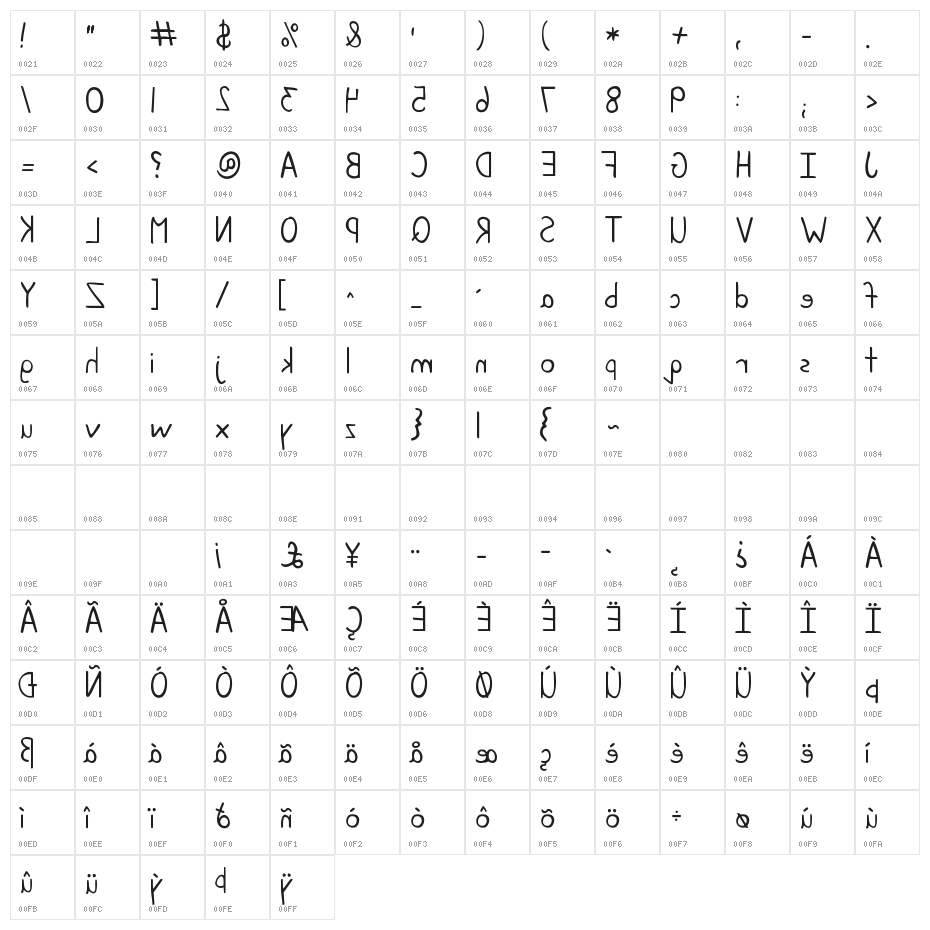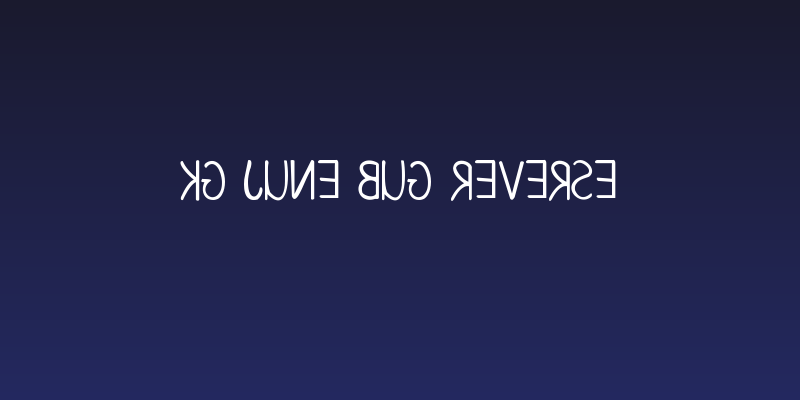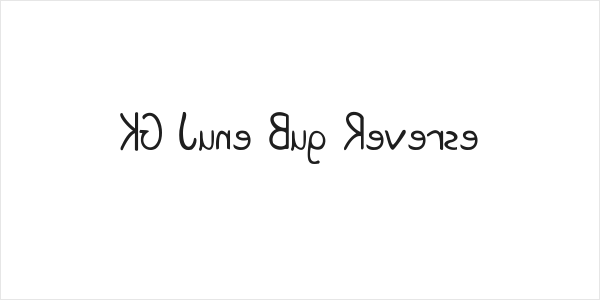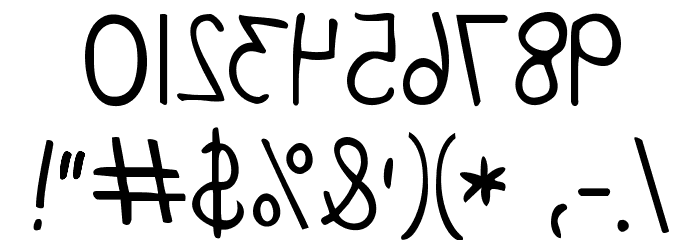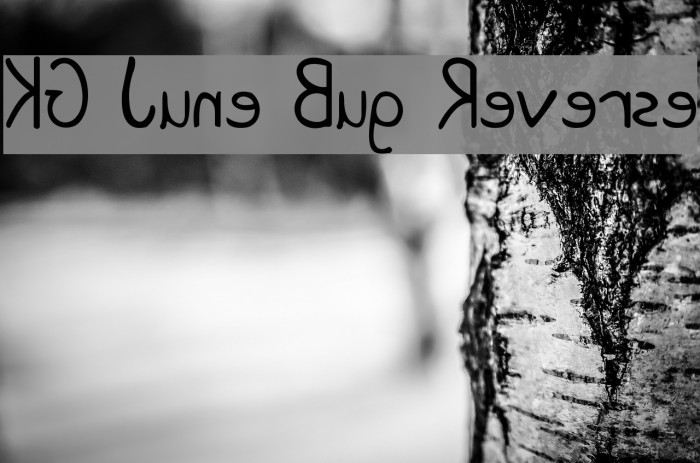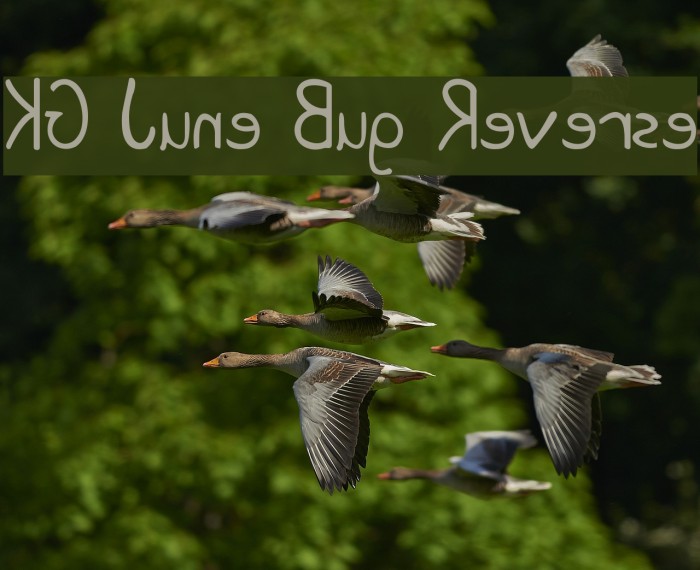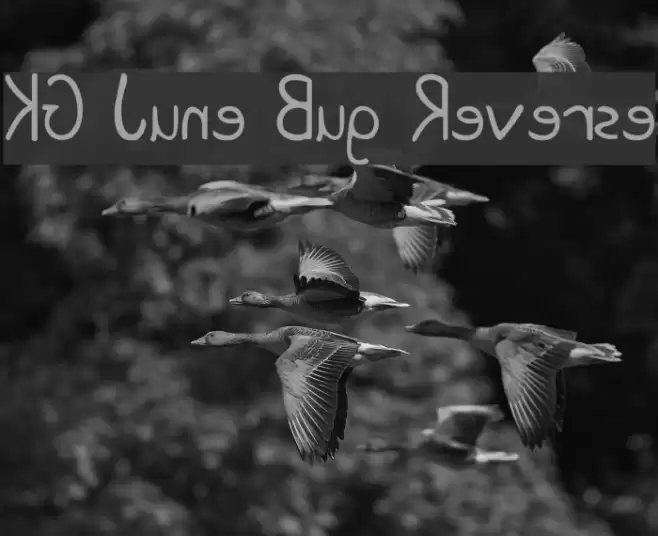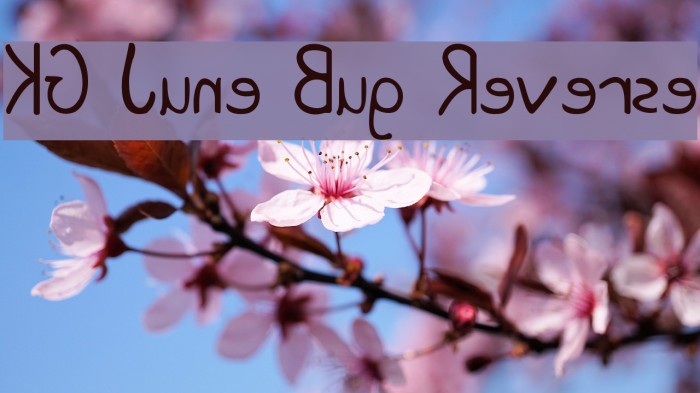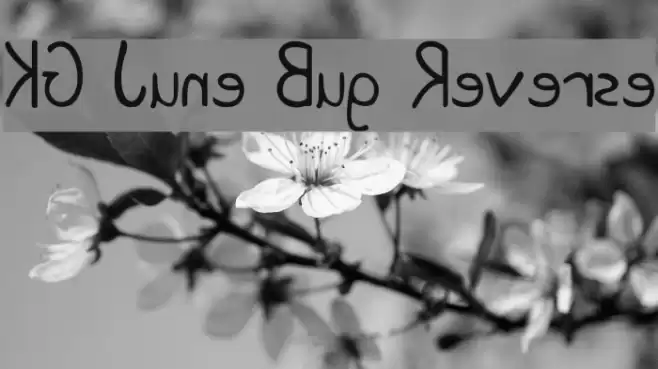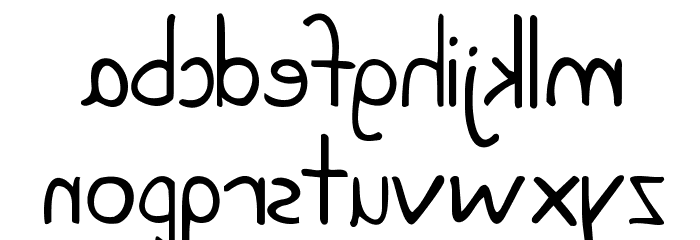
KG June Bug Reverse Font
| النمط العام | Whimsical |
| حالة الاستخدام | Headlines, Casual text, Invitations |
| مشاريع مقترحة | Ideal for children's books, greeting cards, playful branding, and casual invitations. |